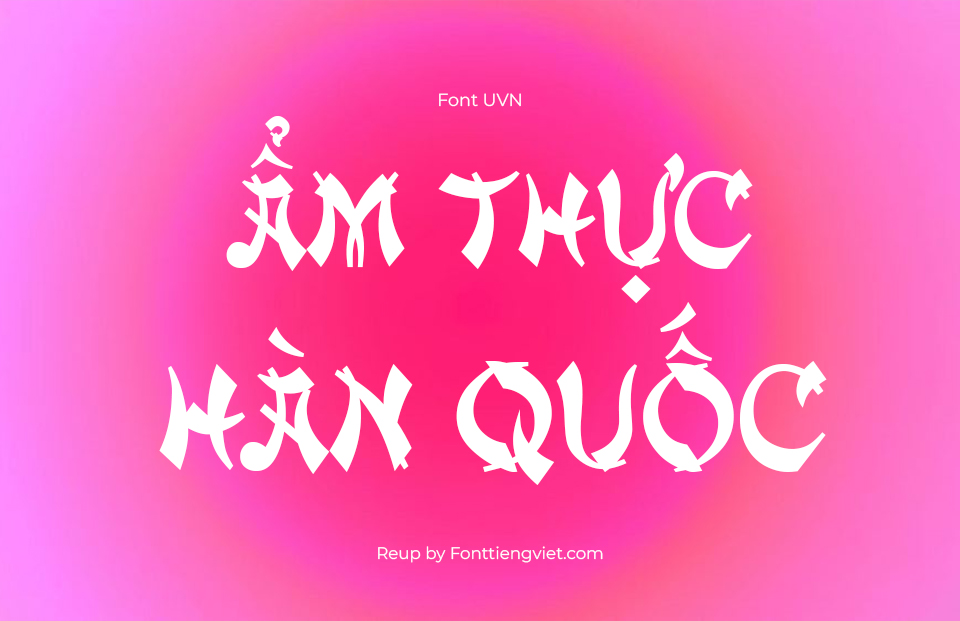
Font Việt Hóa UVN Han Viet
Giới thiệu về Font Việt Hóa UVN Han Viet
Trong thế giới đồ họa, việc tìm kiếm một bộ Font Việt Hóa UVN Han Viet chất lượng là điều vô cùng quan trọng đối với các nhà thiết kế yêu thích nét đẹp truyền thống. Đây là một trong những bộ Font Miễn Phí tiêu biểu nằm trong dự án UVN, được tinh chỉnh để phù hợp hoàn hảo với bảng mã Unicode. Kiểu chữ này mô phỏng đường nét uyển chuyển của bút lông, mang đậm dấu ấn văn hóa Á Đông và tâm hồn Việt. Với sự kết hợp giữa tính cổ điển và hiện đại, font chữ này giúp các tác phẩm trở nên thanh thoát, trang trọng nhưng vẫn đảm bảo sự gần gũi với người xem Việt Nam.
Đặc điểm nổi bật của Font Việt Hóa UVN Han Viet
Phong cách thư pháp ấn tượng
Bộ Font Việt Hóa UVN Han Viet sở hữu những nét thanh nét đậm rõ rệt, tạo cảm giác như được viết tay bởi các bậc thầy đồ thư. Cấu trúc chữ được thiết kế cân đối, giúp người dùng dễ dàng ứng dụng vào nhiều loại hình sáng tạo khác nhau.
Khả năng ứng dụng đa dạng
Người dùng có thể sử dụng font chữ này để thiết kế thiệp chúc mừng, bìa sách văn học, các câu đối Tết hay tiêu đề cho các video về lịch sử. Đặc biệt, đối với các bạn học sinh và giáo viên, đây là công cụ đắc lực để trang trí báo tường hoặc làm slide bài giảng về văn hóa dân gian thêm phần sinh động.
Kết luận về bộ chữ UVN Han Viet